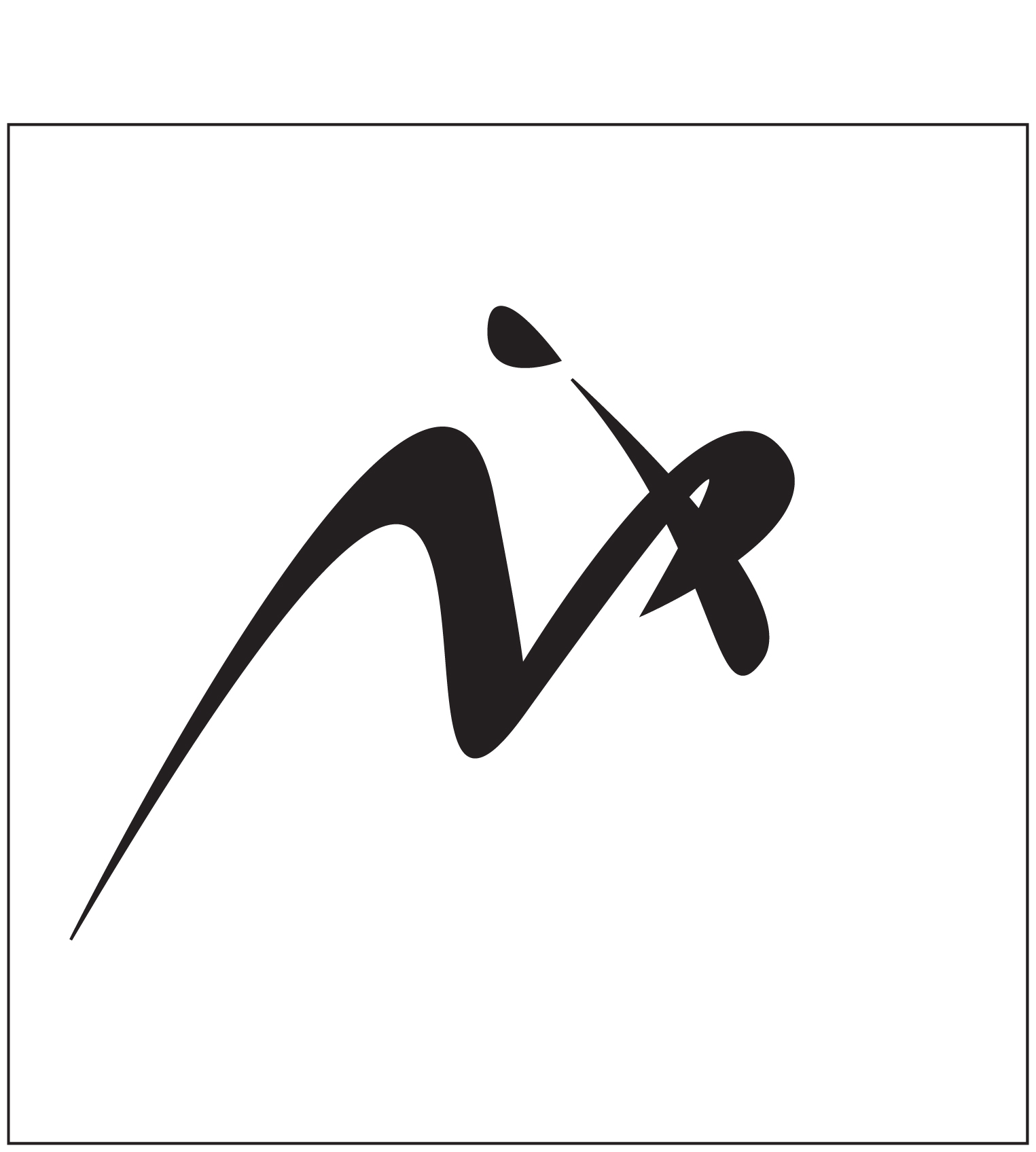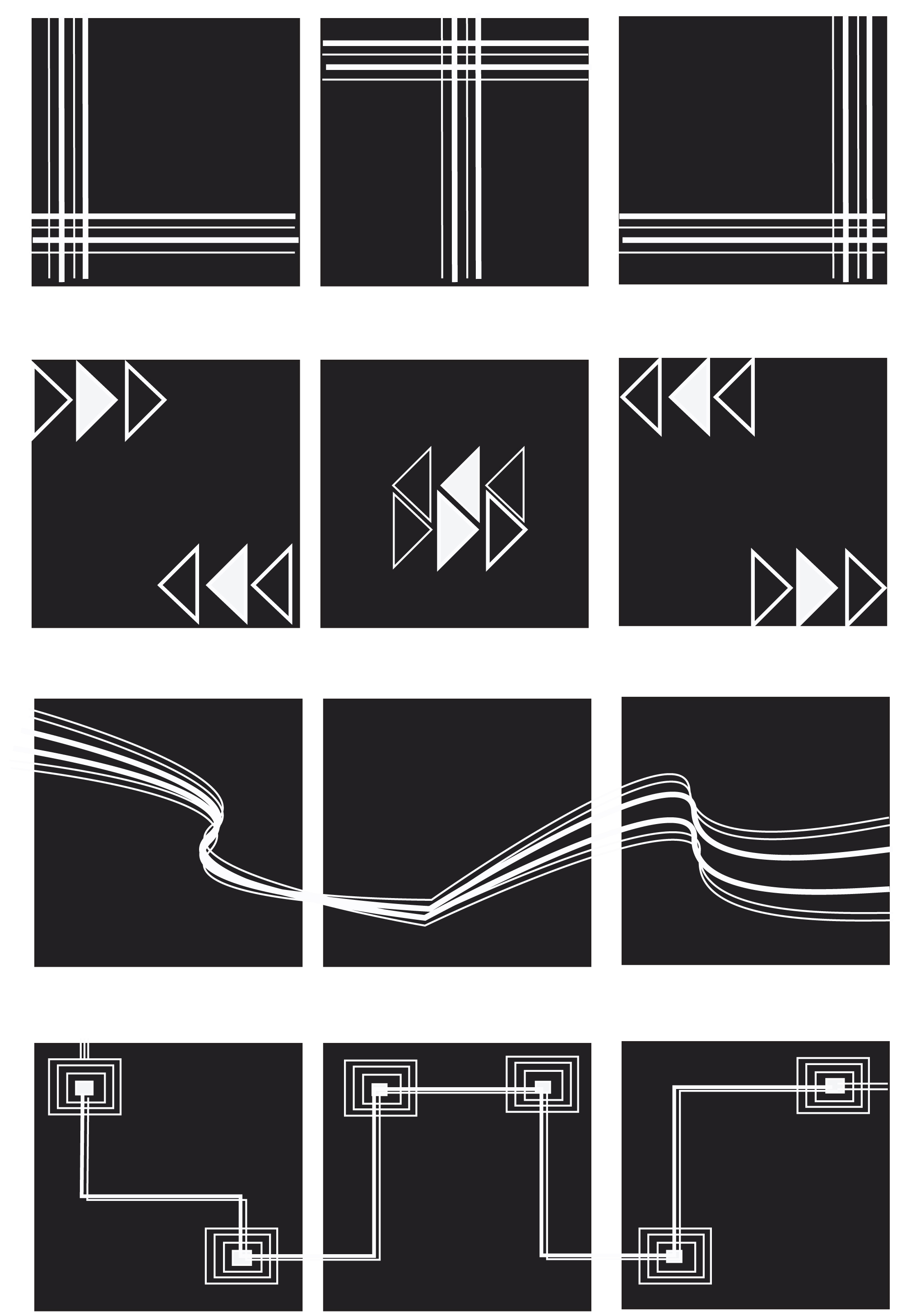
งานส่งอาจารย์ครับ
ให้ทำฟอร์มรูปแบบเดียวกัน ให้ดูเหมือนเคลื่อนที่ได้
งานทำตัวอักษร วิชาเดียวกันครับ วิชา Desktop Publishing ครับ
ทำคำ มาเล่น ให้เข้ากับความหมาย
คำว่า CYCLE ครับ วงกลม
มีอีกหนึ่งอย่าง เรื่องเดียวกัน แต่เป็นคำว่า Move ครับ